2023 年 22 种最佳新艺术风格字体(免费和付费)
已发表: 2023-10-01您是一名平面设计师,希望为您的项目增添一丝优雅和精致吗?
或者您可能只是对新艺术风格字体以及它们如何增强您的设计工作感到好奇?
那么,您来对地方了! 在这篇博文中,我们将探讨新艺术风格字体的美丽和独特性,以及它们如何将您的设计提升到一个新的水平。
现在,您可能想知道,新艺术风格字体到底是什么? 别担心,我们已经为您提供了保障。
新艺术风格是一种流行的设计风格,起源于19世纪末,其特点是受自然启发的有机、流动的形式。 在排版方面,新艺术风格字体以其复杂的细节、精致的曲线和装饰元素而闻名。
它们捕捉了这一艺术运动的精髓,可以为任何设计带来优雅和精致的感觉。
但为什么要考虑在项目中使用新艺术风格字体呢? 好吧,让我们看一些统计数据和事实。
您是否知道排版在整体设计和视觉传达中起着至关重要的作用? 事实上,研究表明字体选择会影响设计的情绪、可读性和整体感知。
通过将新艺术风格字体融入您的项目中,您可以唤起一种怀旧、优雅和独特的感觉。
在本文中,我们将仔细研究一些最流行的新艺术风格字体以及如何在您的设计工作中最好地利用它们。
无论您是要创建复古风格的徽标、设计婚礼请柬,还是只是为数字艺术作品增添一丝魅力,新艺术风格字体都可以提供多种选项来满足您的需求。
因此,事不宜迟,让我们深入了解新艺术风格字体的世界,了解它们如何将您的设计提升到新的高度。
最佳优质新艺术风格字体
希望使用一些令人惊叹的新艺术风格字体来提升您的图形设计项目? 别再犹豫了!
在本节中,我们精选了最好的优质新艺术风格字体,它们一定会为您的设计增添一丝优雅和精致。 立即查看这些必备字体并释放您的创造力!
万苏拉
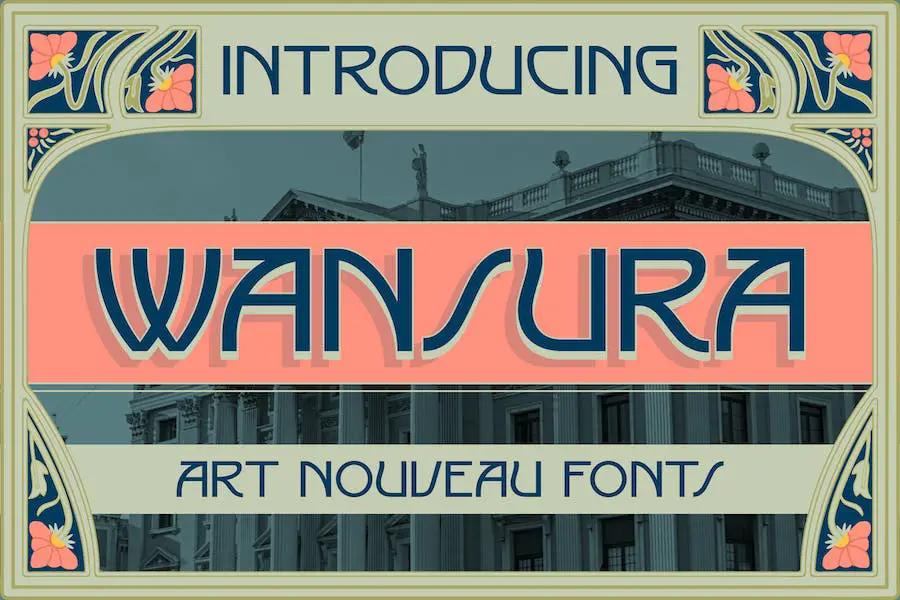
Wansura 是一种基于新艺术风格的字体,从新艺术风格优雅而复杂的设计中汲取灵感。
这款 Google 新艺术风格字体不仅美观,而且用途广泛,非常适合各种设计项目,例如徽标、品牌、标牌、装饰、书籍、封面、徽章和徽章、服装、服饰、商品、电影标题、和连续剧。
Wansura 字体以其复杂的装饰性视觉效果捕捉了新艺术时代的精髓。 它散发着精致和优雅的感觉,使其成为那些希望为其设计项目增添永恒之美的人们的完美选择。
Wansura 的新艺术风格设计为您的项目带来怀旧感和复古魅力。
艾洛迪
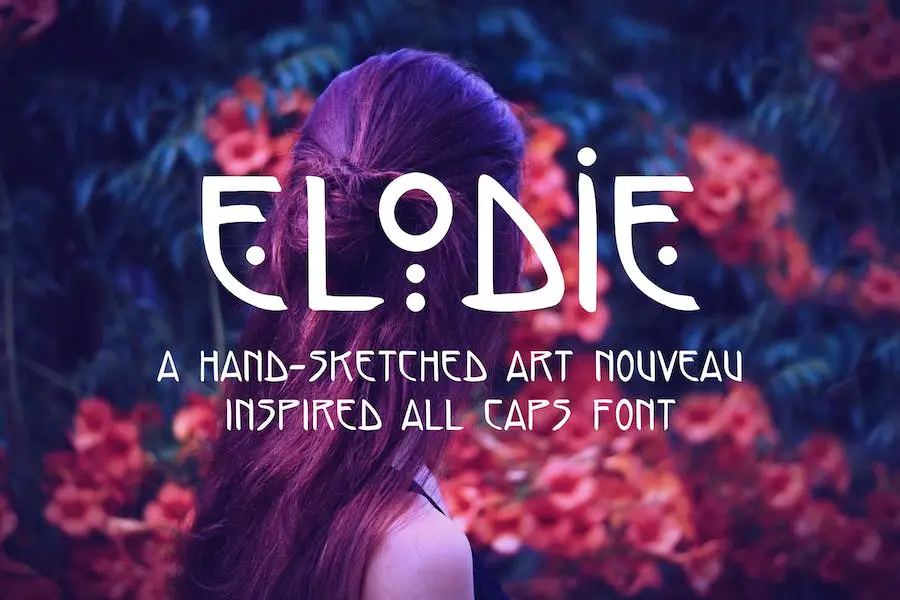
Elodie 是一款多功能字体,专为希望以独特的方式增强其项目的图形设计师而设计。
这款 Adobe 新艺术风格字体支持多种欧洲语言,具有用毛笔创建的古怪手绘字符。
非常适合标题、简短引用和产品名称,您可以使用小写字母作为常规文本,并通过合并大写部分的字符来为您的写作添加一些特殊的怪癖。 拥抱 Elodie 的魅力,为您的设计增添独特的风格。
朴素的
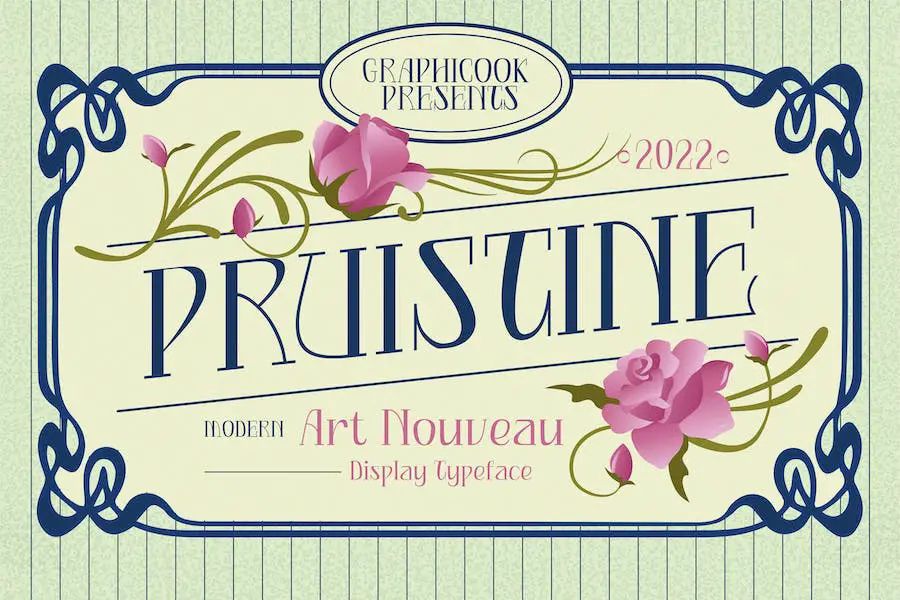
Pruistine 是一款令人印象深刻的显示字体,从新艺术风格优雅而复杂的设计中汲取灵感,同时融入了现代风格。
这款 Word 新艺术风格字体是创建迷人标题、包装设计、杂志布局、徽标等的理想选择。 该字体的装饰元素和独特的风格将毫不费力地增强任何项目并使其脱颖而出。
它的多功能性使其可用于各种创意应用程序,确保您在设计工作中找到它的完美用途。
桃色幻想
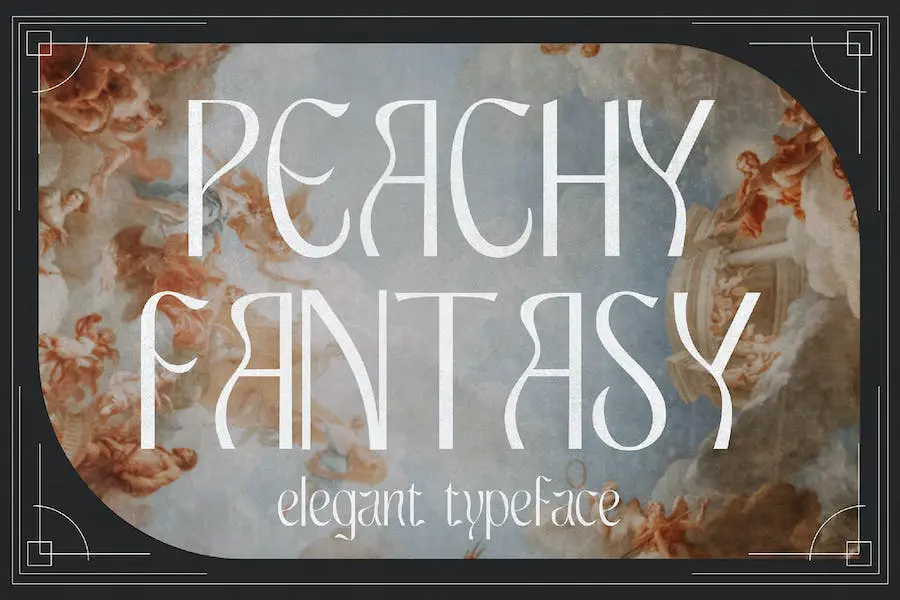
Peachy Fantasy 字体是一种新艺术风格的字体,可为您的设计项目带来怀旧感。
这款 Canva 新艺术风格字体非常适合杂志、海报、品牌、服装等,为您的创作带来优雅和原创的触感。
凭借其复古影响力和现代感,Peachy Fantasy 是希望为自己的作品增添一丝怀旧气息的平面设计师的必备之选。
盖茨比
Gatsby 提供装饰艺术复古风格,非常适合各种项目,为您的设计增添一丝优雅。 无论您从事现代还是复古/复古项目,这种字体一定会增强您的创造力。
凭借其一系列的字体选项和复古风格的美感,这款 Cricut 的新艺术风格字体对于希望提升其项目的图形设计师来说是一个宝贵的工具。
其现代与复古元素的结合使其适合广泛的设计应用。 通过包含垃圾和内联变体,您可以触手可及的更多创意可能性。
丰塞卡
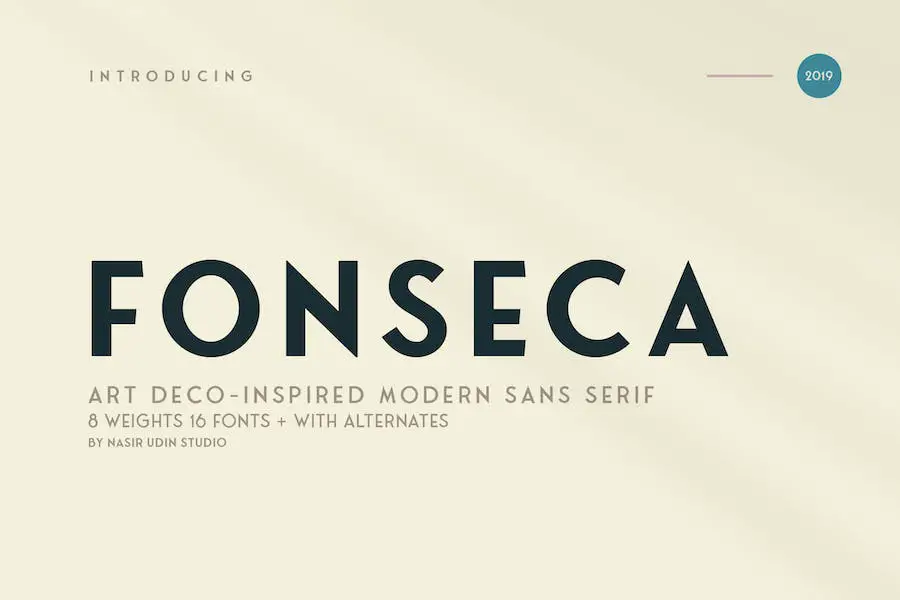
Fonseca – 现代化的复古字体,为您的设计项目增添一丝优雅气息。 无论您是在制作旅游手册、历史杂志还是文化品牌项目,这个展示系列都是完美的选择。
凭借其时尚简洁的设计,它非常适合创建引人注目的标题、海报、徽标和包装。
受到 20 世纪初装饰艺术和版式海报的启发,这款新艺术风格的 Tattoo 字体将简单的几何形式与现代化的字母形式相结合,创造出真正独特且引人注目的字体。
新艺术风格
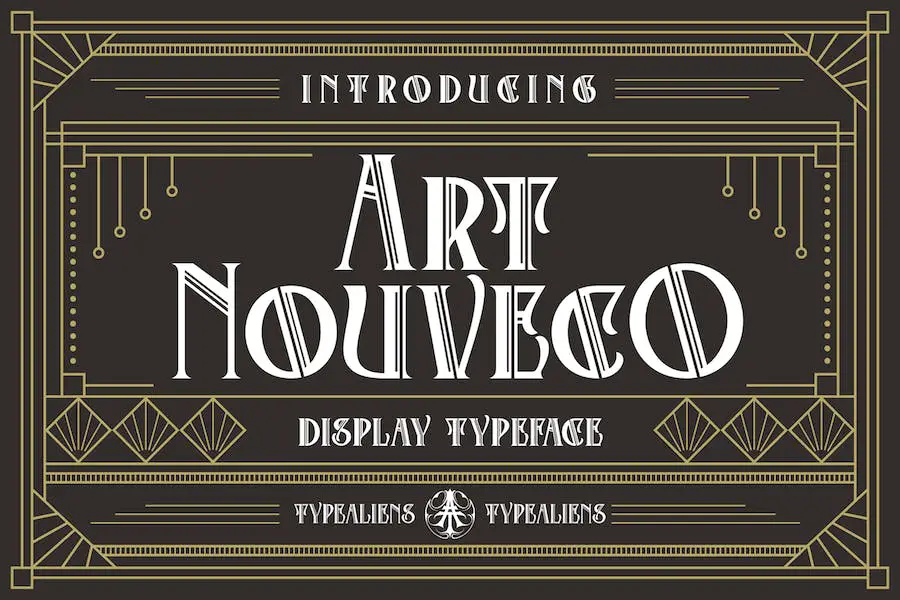
新艺术风格是新艺术风格和装饰艺术字体的迷人融合,为任何设计项目增添了独特和时尚的触感。
这种字体受到装饰艺术的轻微阳刚影响,在优雅和精致之间取得了完美的平衡。 它毫不费力地将经典装饰艺术风格与微妙的优雅融为一体,使其成为创造优雅和永恒设计的完美选择。
新艺术风格融合了新艺术风格和装饰艺术元素,使其有别于其他字体,为您的项目带来独特且引人注目的美感。
其优雅的曲线和精致的细节为任何文本或标题增添了一丝精致,立即提升了整体设计。
无论您是从事品牌推广、邀请函还是任何其他创意工作,这款新艺术风格海报字体一定会给人留下深刻的印象。
德乔·罗森
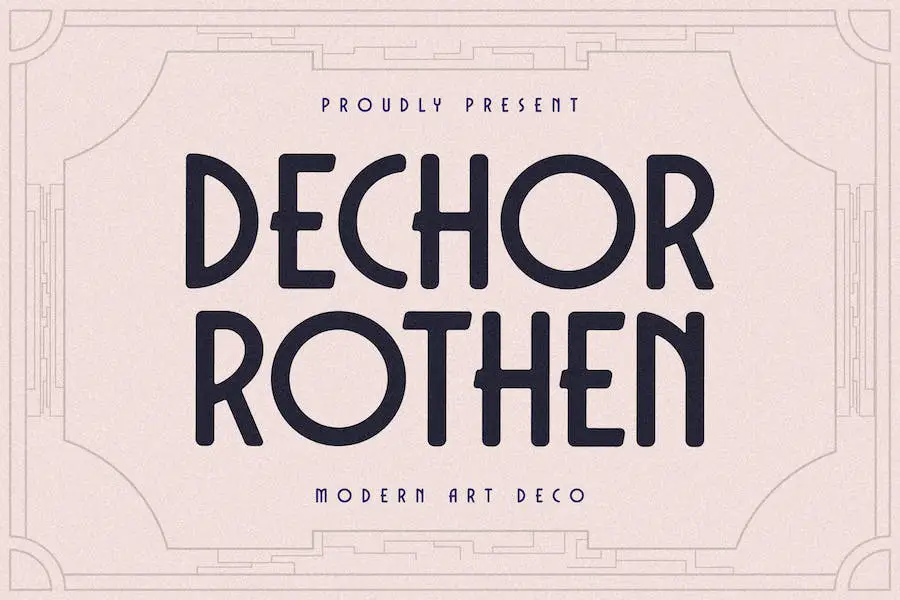
Dechor Rothen 是一种旨在增强图形设计项目的视觉吸引力的字体。 无论您是在制作海报、社交媒体帖子、品牌材料还是个人项目,这款字体都能满足您的需求。
凭借其多功能性和现代风格,它是为您的设计增添优雅和创造力的完美选择。
其多功能性还使其能够适应各种设计风格,无论您想要现代、简约的外观还是复古、装饰艺术风格的美学。
滚动艺术
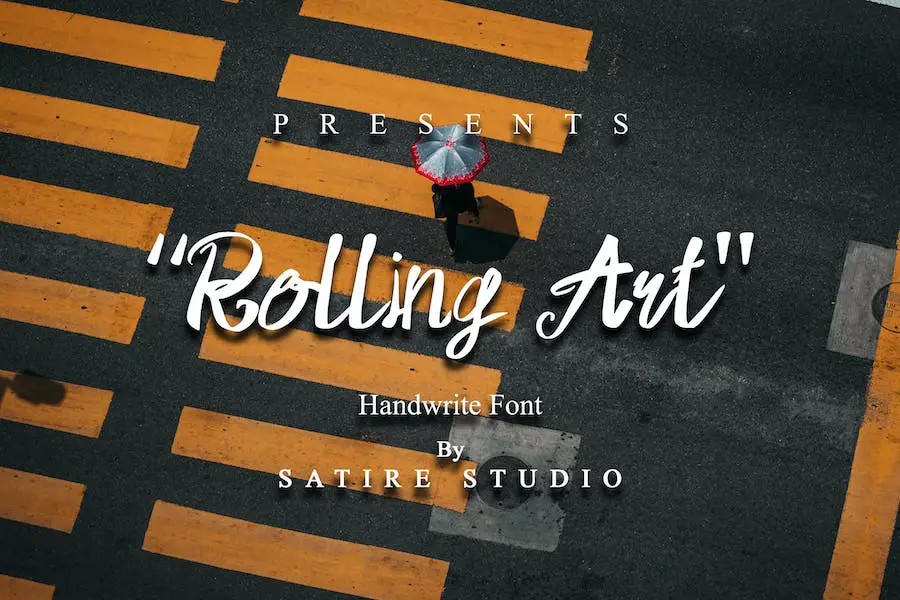
凭借其装饰风格,滚动艺术为各种设计增添了一抹美感。 它非常适合创建令人惊叹的邀请函、贺卡、品牌材料、名片、引言、海报等。 其独特和艺术的外观将使您的项目脱颖而出。
用滚动艺术的优雅和魅力升级您的项目。 它的易访问性和用户友好性使其成为寻求提升设计的图形设计师的必备字体。
阿拉亚
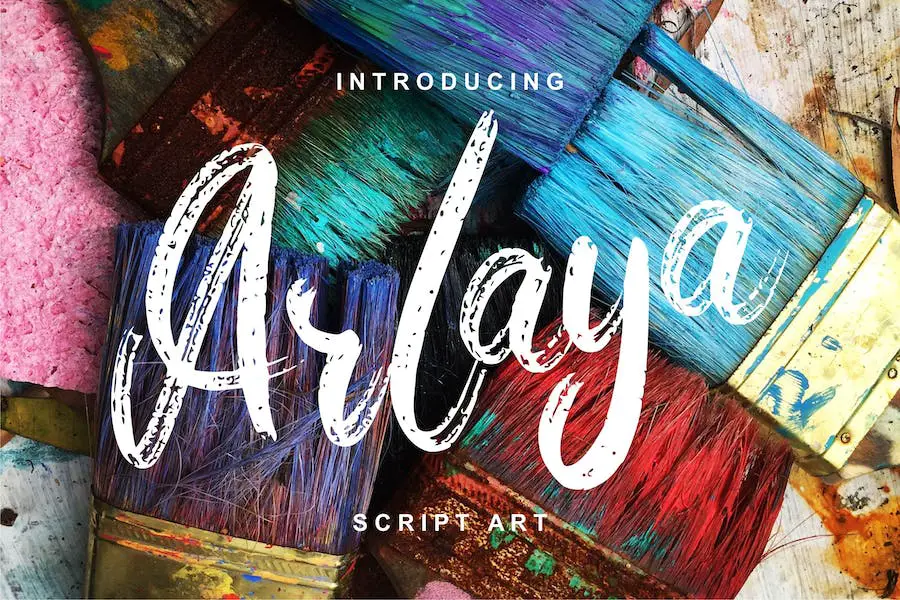
Arlaya 是一款令人惊叹的脚本艺术字体,体现了书法的优雅。 它非常适合为您的项目增添一抹美感,无论是邀请函、贺卡、品牌材料、名片、报价单、海报等等!
凭借其广泛的替代字符和 Open Type 功能,例如风格集、风格替代、上下文替代、SWASH 和连字,您拥有无限的可能性来定制您的设计。
另外,这款 Timeless Look 的新艺术风格字体具有 PUA Unicode,这意味着所有替代字符都经过特殊编码,可以轻松完整访问。 Arlaya 是任何设计师收藏中的必备单品。
安格维
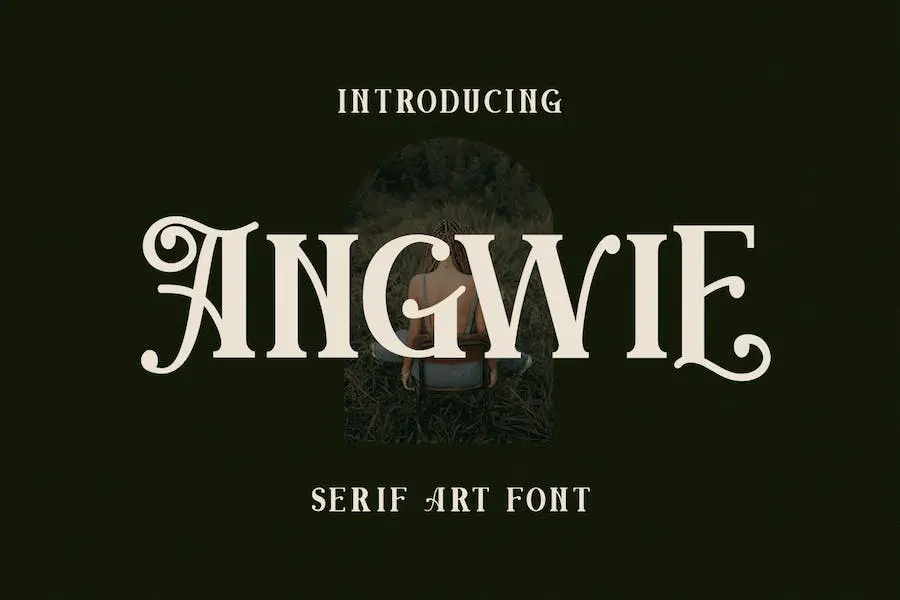
Angwie 是一款美丽的字体,结合了现代和经典的排版,为您的项目带来独特而优雅的触感。
其手工制作的现代维多利亚手写风格增添了迷人和怀旧的感觉。 凭借其出色的替代和连字,Angwie 使您能够创造出引人注目的令人惊叹的设计。
无论您使用的是 PC 还是 Mac,安装 Angwie 都非常简单且无忧。 安装后,您可以立即开始使用该字体来增强您的图形设计项目。 这款适合艺术家的新艺术风格字体可与流行的设计软件无缝配合,让您轻松释放创造力。
Angwie 的多功能性使其适合广泛的设计应用。 无论您是在制作徽标、海报、网站还是任何其他需要排版的项目,Angwie 都会提升您的设计并使其在视觉上引人入胜。
其现代与经典元素的独特融合将帮助您的作品在通用字体的海洋中脱颖而出。
装饰地带
Strip Deco 是一款从优雅精致的装饰艺术风格中汲取灵感的展示字体。 它具有严格的线条和简洁的设计,非常适合各种创意项目。
这种字体同时包含大写和小写字母以及数字、标点符号和符号,具有多功能性和灵活性。
它还包括替代字符,让您可以为您的设计添加独特的风格。 无论您是在制作徽标、T 恤、海报还是社交媒体图形,Strip Deco 都一定会增强您的项目并做出大胆的声明。
德阿洛伊
De Arloy 是一种从 19 世纪末至 20 世纪初的新艺术风格中汲取灵感的字体。
它结合了经典的版式和现代功能,为任何设计项目带来优雅的感觉。 这种字体特别适合大型显示器或短文字,尽管它也适用于正常大小的文本。
除了大写字母选项外,De Arloy 还包括小写字母,这为其使用增添了更多灵活性。 无论您正在进行品牌项目、营销活动还是任何其他设计工作,此字体都可以帮助您将工作提升到一个新的水平。
凭借对新艺术风格的认可和广泛的应用,De Arloy 是寻求以优雅和精致的方式增强其项目的平面设计师的必备工具。
其多功能性和迷人的美感使其成为任何设计师字体收藏的宝贵补充。 那么为什么不尝试一下,看看它如何改变您的设计呢?
波赫特
POCHTER 是一种将装饰艺术的优雅与其大写和小写字母、标点符号和数字相结合的字体。
借助其 OTF 和 TTF 文件,您可以轻松地将这种字体合并到您的项目中。 此外,它还提供多语言支持,确保您可以用任何语言创建令人惊叹的设计。
这种字体的灵感来自装饰艺术风格,以其流畅的线条和几何形状而闻名。 无论您是在设计徽标、海报还是网站设计,POCHTER 都可以增添一丝精致和精致。
同时包含大写和小写字母可以让您的设计具有更大的多功能性。 您可以尝试不同的字体风格并创建真正脱颖而出的独特组合。
为了迎合不同的语言和书写系统,POCHTER 提供多语言支持。 无论您的客户或受众来自世界哪个地区,您都可以自信地创建能够有效、直观地进行交流的设计。
教区展示
Rectory Display 是一款多功能字体,可为您的项目带来当代装饰艺术风格的设计。
该字体具有广泛的语言支持,包括南非荷兰语、阿尔巴尼亚语、加泰罗尼亚语、丹麦语、荷兰语、英语、法语、德语、意大利语、挪威语、葡萄牙语、西班牙语、瑞典语和祖鲁语,非常适合覆盖全球受众。
教区展示的与众不同之处在于其独特的特征和古怪的连字,让您可以为您的设计增添一丝个性。
无论您是在设计杂志标题和布局、徽标和品牌、邀请函、引言、博客标题、海报还是广告,这种字体一定会让您的作品脱颖而出。
最佳免费新艺术字体
希望为您的设计项目增添一丝优雅和美丽? 我们精心挑选的最佳免费新艺术风格字体就是您的最佳选择。
这些令人惊叹的字体将立即提升您的设计并吸引您的观众。 不要错过它们可以为您的创作带来的魔力 - 看看下面我们的首选!
新艺术风格帽子
对于寻求提升项目设计的图形设计师来说,新艺术风格 Caps 是一个绝佳的字体选择。
这款免费字体由 Dieter Steffmann 创建,以其复杂而优雅的字体捕捉了新艺术运动的精髓。
新艺术风格 Caps 的突出特点之一是它完全免费使用。 对于预算紧张或只想在没有任何财务承诺的情况下尝试新字体的设计师来说,这是个好消息。
新艺术风格帽子的多功能性是使其备受平面设计师青睐的另一个因素。
无论您是在制作海报、徽标、网站还是任何其他设计项目,这种字体都可以增添一丝优雅和精致。 其独特的字体脱颖而出,可以帮助您的设计产生强大的视觉冲击力。
萨布尔瓦
Sabrva 是一种为您的版式设计增添经典气息的字体。 借助多达 7 种替代字母变体,您可以轻松自定义文本。 该字体由 Nirmana Visual 创建,旨在成为完美的伴侣或强大的独立字体。
Sabrva 以其经典的风格为您的项目带来独特而永恒的外观。 替代字母变体可以增加您设计的多功能性和创造力。
无论您喜欢更优雅、精致的风格,还是更大胆、更具戏剧性的风格,Sabrva 都能满足您的需求。
Sabrva 的亮点之一是它能够很好地作为补充字体或独立字体。
它与其他字体无缝融合,创造和谐的视觉效果。 另一方面,它也可以作为主要字体保持其地位,吸引注意力并为您的设计增添与众不同的感觉。
马尔文
Malven 是一款设计精美的字体,可以极大地增强您的项目设计。 凭借其优雅而复杂的新艺术风格,该字体为任何创意作品增添了一丝精致和独特。
马尔文的属性确实非常出色。 字母的细致流畅的线条营造出动感和优雅的感觉,非常适合需要一丝优雅的设计。
此外,该字体独特的曲线和装饰增添了一定令人印象深刻的复古魅力。
Malven 的突出特点之一是它能够捕捉新艺术运动的精髓。
这种字体向 19 世纪末和 20 世纪初的标志性风格致敬,同时仍然保持现代魅力。 对于希望为自己的作品增添怀旧或复古气息的设计师来说,这是一个完美的选择。
阿加卡时尚
Argaka Fashion 是一款专为希望增强项目设计的图形设计师设计的字体。
这种新艺术风格字体为任何设计带来优雅和精致的感觉,非常适合创造迷人的视觉效果。
凭借其曲线美的字母和复杂的细节,Argaka Fashion 为您的设计增添了独特的艺术元素。
无论您是在制作徽标、网站还是印刷广告,这种字体都会让您的项目脱颖而出。
Argaka Fashion 的另一大特点是它的可读性。 尽管其设计复杂,但即使在较小的尺寸下,字体仍然清晰易读,确保您的信息易于被受众理解。
这在排版方面尤其重要,因为可读性在有效沟通中起着至关重要的作用。
新风格
Nouveau 是由 Alan Cairns 设计的字体,已获得免费软件许可并用于非商业用途。 这意味着您可以将其用于个人项目,而不必担心任何许可费用或限制。
该字体具有美丽的新艺术风格,非常适合希望为其项目添加一丝优雅和复古风格的图形设计师。
使用 Nouveau,您可以轻松改进您的作品的设计,并赋予它们独特而精致的外观。 对于任何想要在设计中实现永恒和艺术感的人来说,这是一个不错的选择。
华帝
Creatype Studio 的 Vantage 是一款免费软件、非商业字体,非常适合任何希望增强项目设计的图形设计师。 它具有独特的属性,使其从其他字体中脱颖而出。
Vantage的突出特点之一是其艺术性和优雅的新艺术风格。 这种字体给任何设计带来一丝精致,并增添经典、复古的感觉。
其复杂的细节和流畅的线条使其成为创造引人注目的标题或为任何项目增添一丝优雅的绝佳选择。
除了其美观和多功能性之外,Vantage 还可以免费使用。 作为一种非商业字体,它允许设计者使用它而无需任何许可费用或限制。
这使其成为自由设计师或从事个人项目的任何人的理想选择。
放克
Funk 由 Buddha Graphix 创建,是一种独特而时尚的字体,非常适合希望增强项目设计的图形设计师。
这种字体为任何设计增添了艺术感和复古感。 其特点包括优雅的曲线、复杂的细节以及与各种设计元素的无缝融合。 凭借其共享软件许可证,设计人员可以在其项目中自由探索和使用 Funk,不受任何限制。
无论是徽标、网站还是宣传材料,Funk 都能为任何设计带来一丝新艺术风格的魅力。
经常问的问题
新艺术风格字体是一种起源于 19 世纪末和 20 世纪初的字体风格。 它们的特点是装饰性和流畅的设计,灵感通常来自花朵、植物和曲线等自然形式。
新艺术风格字体用于各种艺术和商业应用,包括海报、广告和书籍封面。
新艺术风格字体因其复杂而有机的设计而脱颖而出,这使它们有别于其他风格。
这些字体通常具有优雅的字母形式,具有精致的曲线和流畅的线条,模仿大自然中发现的美丽。 这种独特的美学使得新艺术风格字体备受追捧,因为它可以创造出具有复古魅力的视觉上迷人的设计。
新艺术风格字体可以为各种设计项目增添一丝优雅和精致。 它们通常用于品牌、标志设计、邀请函、贺卡和复古风格的图形。
合并新艺术风格字体时,请考虑设计的整体主题和美感,以确保具有凝聚力和和谐的外观。 尝试不同的字体配对和组合,创造出具有视觉吸引力的作品,捕捉这一艺术运动的精髓。
在本文中,我们探索了新艺术风格字体的世界以及它们如何极大地增强您的图形设计项目。
我们讨论了这些字体的独特特征,例如复杂的曲线和有机形状,以及它们如何为您的设计增添优雅和精致的感觉。
通过将新艺术风格字体融入您的作品中,您可以真正提升项目的视觉冲击力和整体美感。